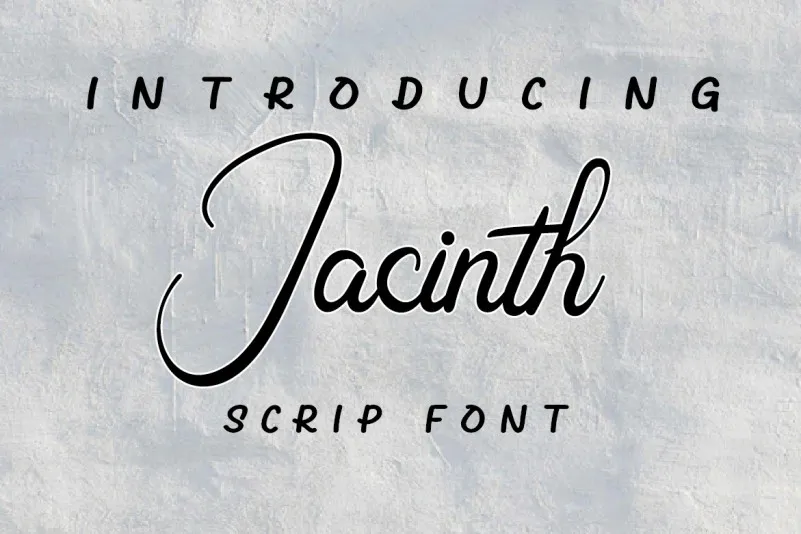
A fonte Jacinth Font é uma escolha perfeita para quem busca um estilo elegante e autêntico, sem perder sua personalidade. Ela transmite confiança, autenticidade e charme de maneira sofisticada, tornando-se a escolha ideal para transmitir mensagens com alma em diversas aplicações. Escreva cards românticos ou presentes personalizados que chamem a atenção, crie marcas devidamente assinados para um negócio confiável e criativo, ou personalize etiquetas de embalagem para dar um toque especial aos seus produtos. Este fonte é perfeito tanto para iniciantes quanto para profissionais que valorizam a personalização e o cuidado no design. Uma das características únicas desta fonte é que ela está PUA (Private Use Area) encoded, facilitando sua utilização por meio de um código privado que permite uma fácil acessibilidade aos todos os símbolos e traços. Este recurso especial a torna versátil e flexível em qualquer projeto gráfico. Jacinth Font é o nome do seu próximo grande trabalho! Essa elegante fonte será uma ótima escolha para aqueles que buscam um design autêntico, sem abrir mão de sofisticação.